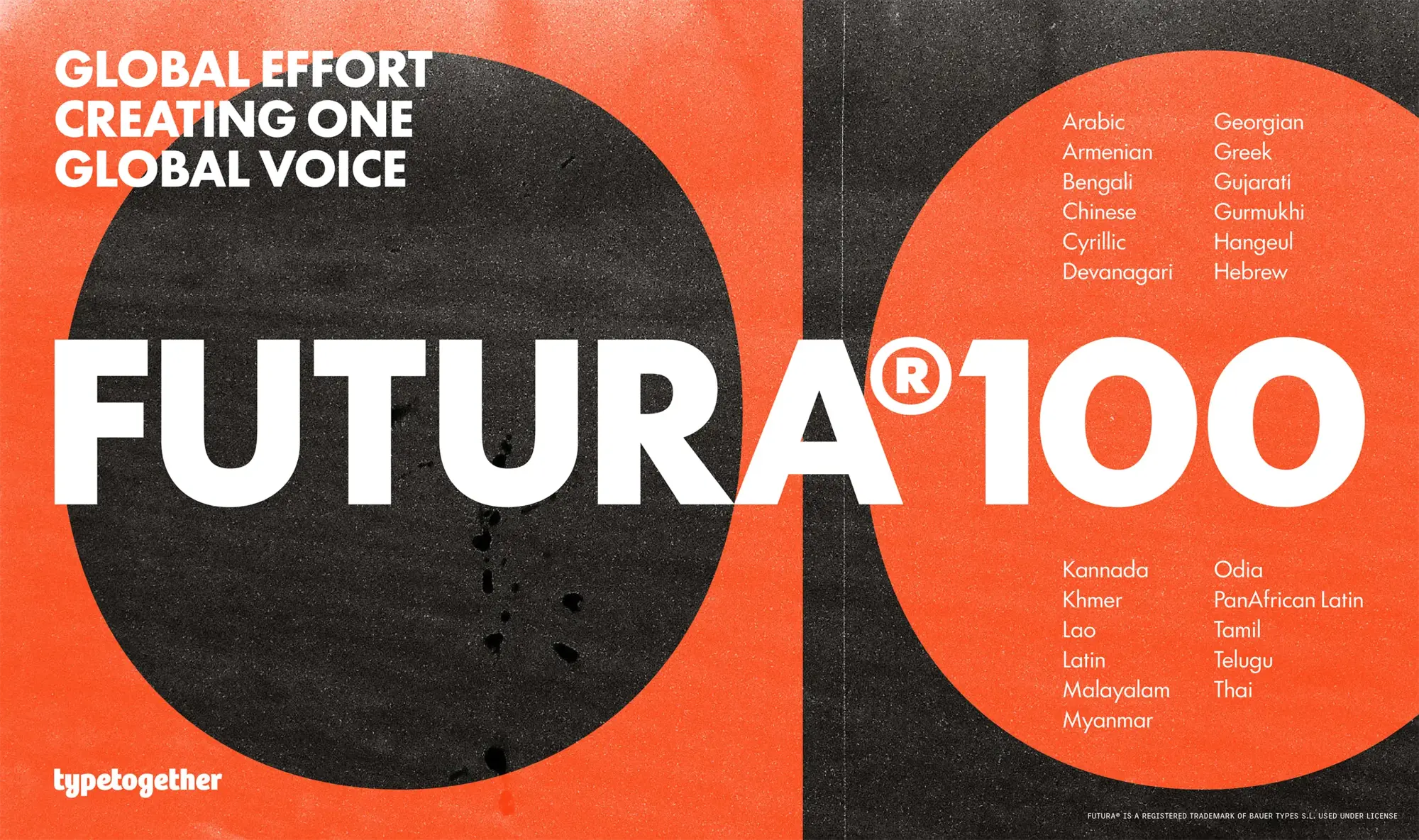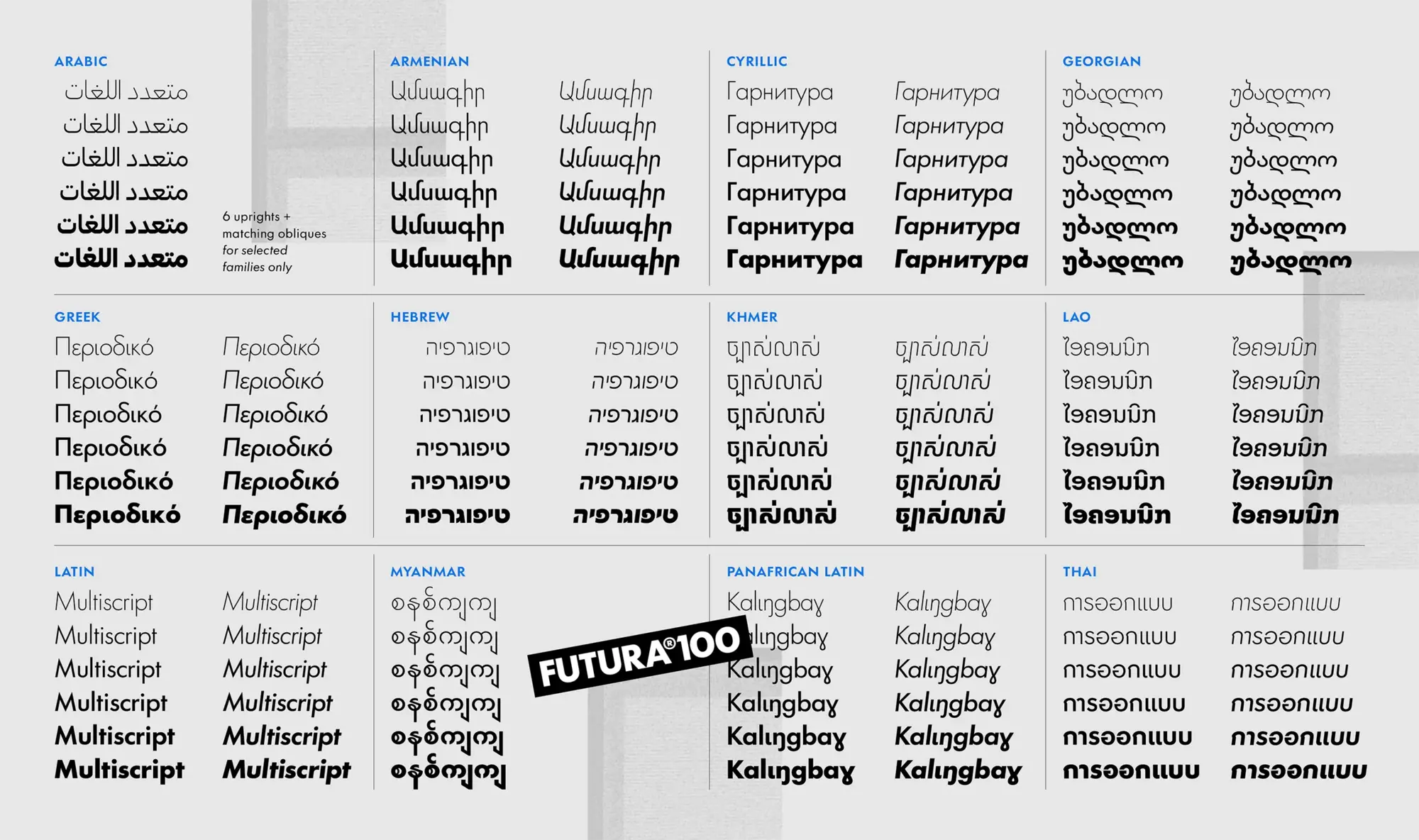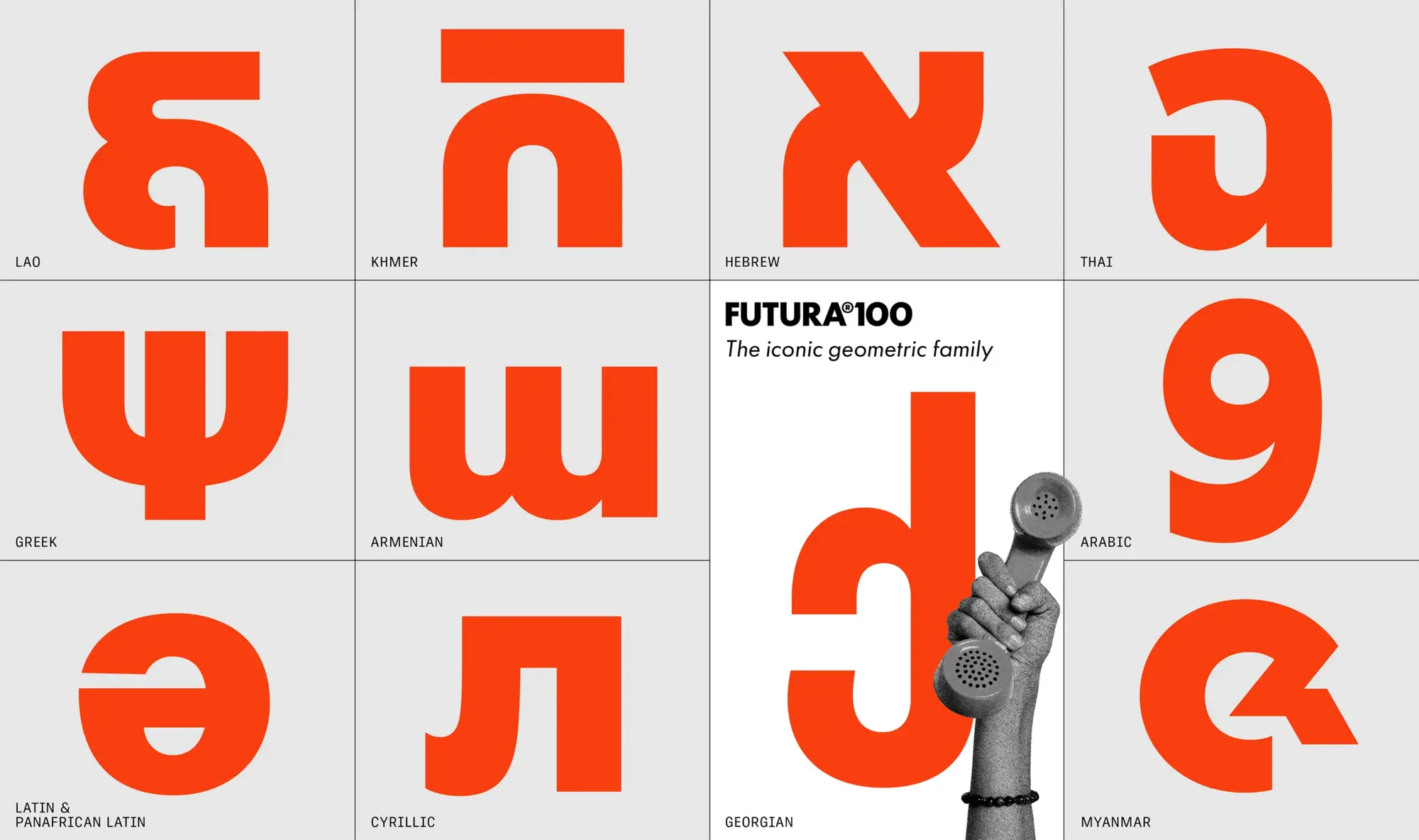
- Antiqua geometrisch
Die Futura 100 ist eine Neubearbeitung der Futura durch Type Together in Zusammenarbeit mit Bauer Types. Die Familie ist auf eine internationale Anwendung ausgelegt und und kommt bereits in der ersten Veröffentlichung mit einer Unterstützung von 12 Schriftsystemen: lateinisch, armenisch, kyrillisch, georgisch, griechisch, hebräisch, khmerisch, laotisch, pan-afrikanisch-lateinisch, thailändisch, arabisch und birmanisch. Weitere 11 Schriftsysteme sind darüber hinaus bereits in Arbeit.